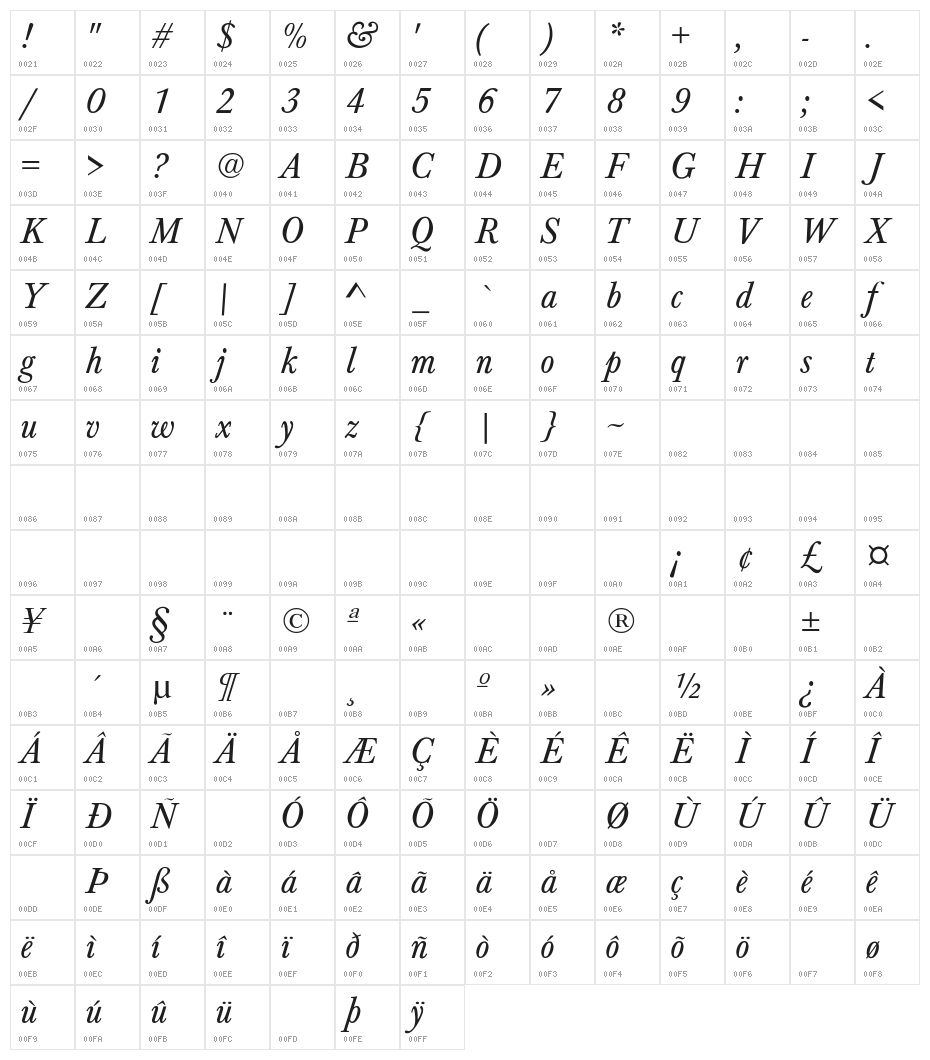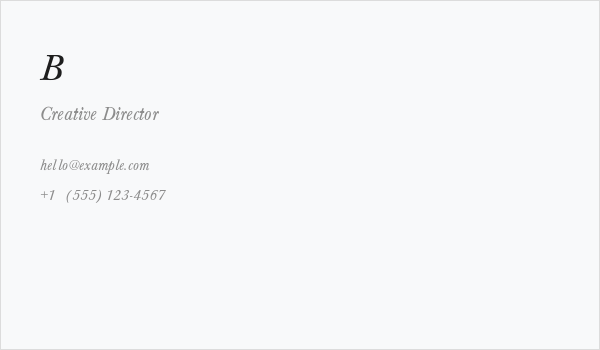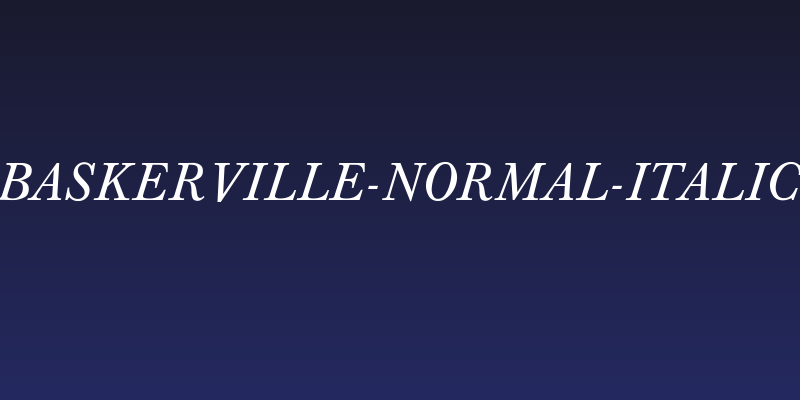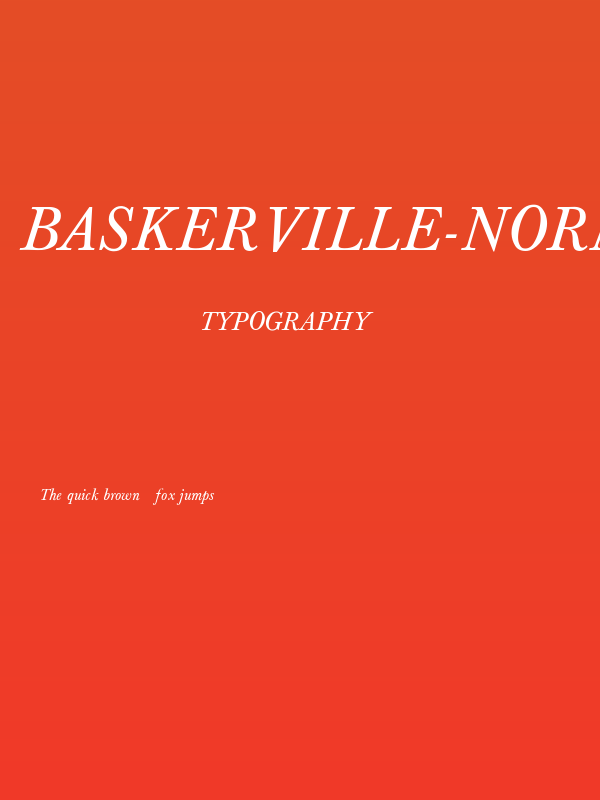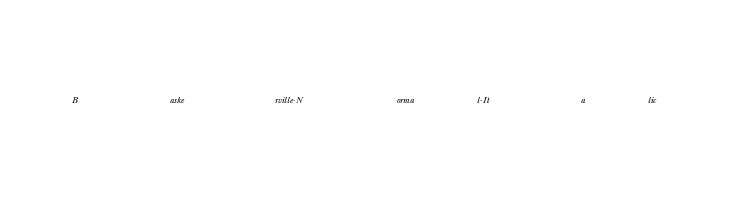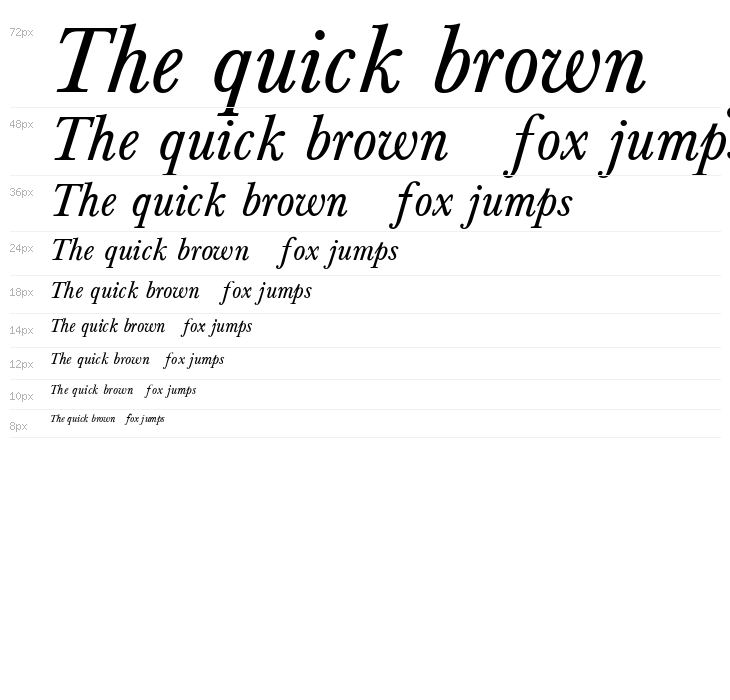
Baskerville-Normal-Italic Font
| Categorías | Serif |
| Estilo general | Classic |
| Caso de uso | Headlines, Body text, Editorial design |
| Proyectos propuestos | Ideal for use in formal documents, invitations, book covers, and editorial design where a touch of elegance and tradition is desired. |